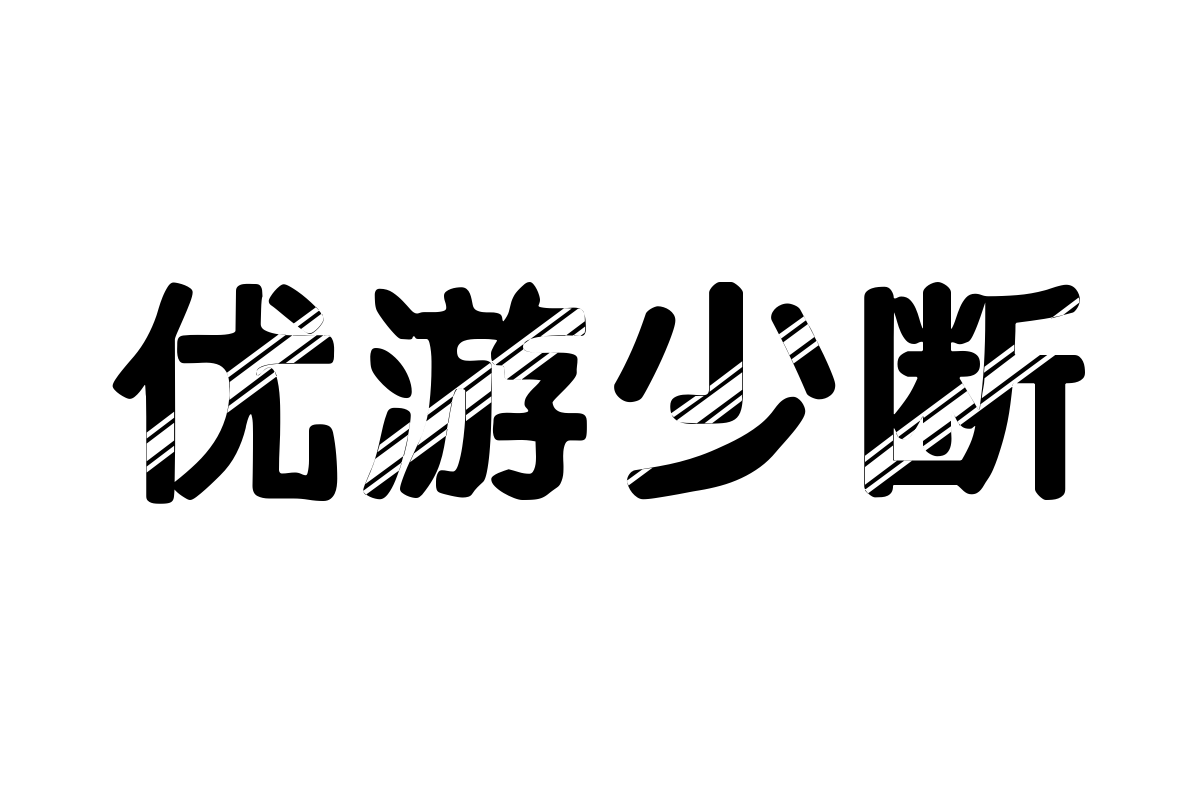
字体管家大侦探体是一款由北京方正字库推出的免费商用字体,具有独特的设计风格和特点。这款字体采用了现代简约的设计理念,线条流畅、字形清晰,适合用于各种需要清晰易读的应用场景。同时,字体管家大侦探体还注重细节处理,如笔画粗细变化、间距调整等,使得整体视觉效果更加协调。此外,这款字体还支持多种字重选择,满足不同场景的需求。总之,字体管家大侦探体是一款实用且美观的免费商用字体。